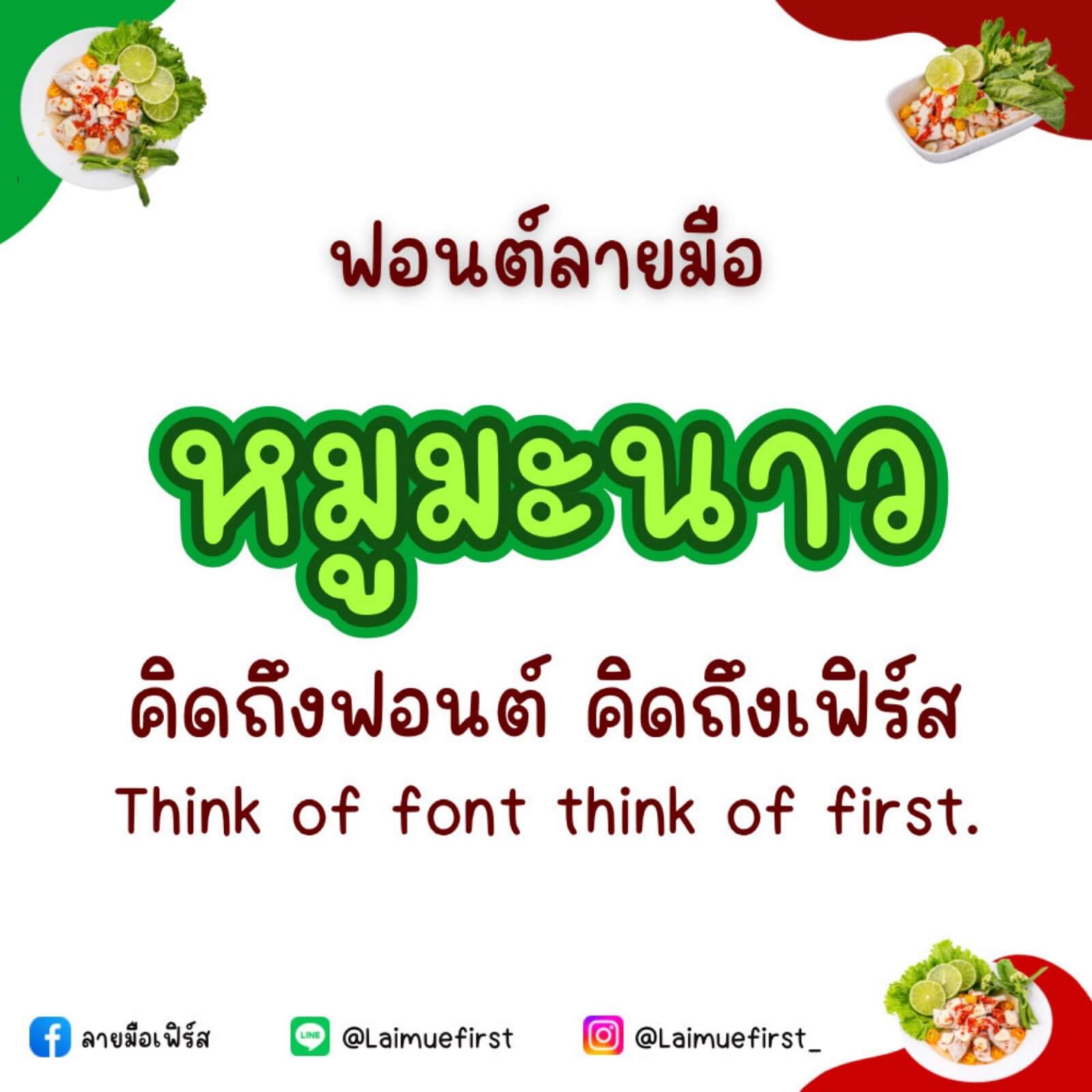
ฟอนต์ลายมือ หมูมะนาว – แจกฟรีสำหรับทดลองใช้งานแบบส่วนตัว เวอร์ชันทดลอง (Demo) ไม่อนุญาตให้นำไปใช้เชิงพาณิชย์นะค้าบบบ
ฟอนต์ 363PANI.ยิ้มหน่อยน้าาา – ตอนเขียนฟอนต์นี้อยากได้ เป็นฟีลคำคม คำใจ เส้นบาง สบายตา แบบอยากได้ฟีลเขียนเอง ตัวไม่เท่ากัน ไม่เรียบร้อย แต่ต้องอ่านง่ายและต้องน่ารัก – ฟอนต์นี้ทำคอนเทนต์สวย ทำคลิป แต่งรูปแนวมินิมัล แนวสดใส ได้หมด
ฟอนต์เจ้าออกัส (บรัชหยัก) – แจกฟรี! ฟอนต์ไม่มีหัว เท็กซ์เจอร์หยักๆ เพิ่มความน่ารักตะมุตะมิ อ่านง่าย สระไม่ลอย ใช้งานได้ทั่วไป เช่น ทำคลิป แต่งปกรูป และอนุญาตให้สร้างผลงานแล้วหารายได้จากน้องได้เลย โหลดไว้ติดเครื่องไว้เลย แนะนำเลยค่ะ!
เอฟซี วิชั่น ไวด์ (FC Vision Wide)
รูปแบบทางเลือกตัวกว้างของฟอนต์ FC Vision Superfamily กว้างขึ้นกว่าปกติเล็กน้อยเพื่อ เปิดพื้นที่ 110% เทียบกับตัวปกติ
เอฟซี วิชั่น เอ็กแพนด์ (FC Vision Expanded)
รูปแบบทางเลือกตัวขยายของฟอนต์ FC Vision Superfamily ขยายให้กว้างกว่าตัวกว้าง 125% เทียบกับตัวปกติ
เอฟซี วิชั่น เอ็กซ์ตราเอ็กแพนด์ (FC Vision ExtraExpanded)
รูปแบบทางเลือกตัวขยายกว้างพิเศษ กว้างที่สุดในของ FC Vision Superfamily กว้าง โปร่ง และสง่างาม สร้างอารมณ์หนักแน่น พร้อมดึงดูดสายตา